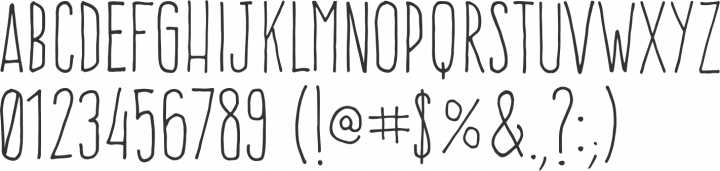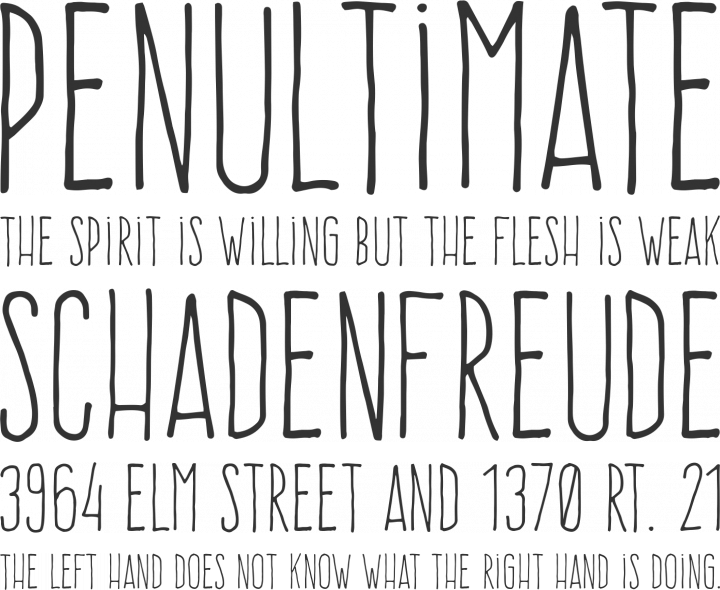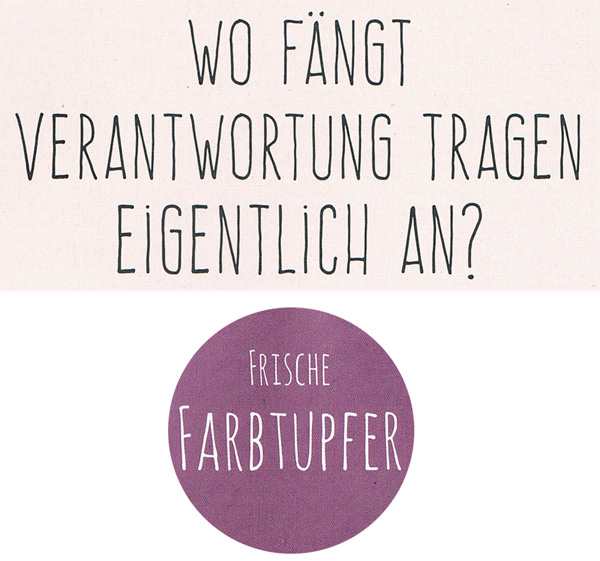
Momentan extrem populären Font gesucht
Kennt wer diesen plakativen Font? Er ist gerade (Frühling 2016) sehr populär und ich sehe ihn eigentlich überall, vor allem auf großflächigen Plakatwänden. Das Bild habe ich von einem aktuellen Aldi Frühlings-Prospekt und von einem aktuellen Rewe Prospekt abgescannt.
Wenn Du bei MyFonts »Liebe Erika« eingibst und dann rechts auf »View all XX fonts« klickst, dann könnte die gesuchte Schrift mit großer Wahrscheinlichkeit bei den angezeigten Ergebnissen dabei sein.
Das ist nach meinen Unterlagen die Frente H1 ... Creative Commons Licence ... keine weiteren Angaben beim Schriftenhörchen ...
Die „Small Caps“ in den Frischen Farbtipfern sollten handgeblasen und mundgemalt sein. Achte auf das I/i und Du siehst was ich meine?
Hier scheint die Homepage von Frente H1 zu sein:
Da findet man aber auch nichts über den Urheber.